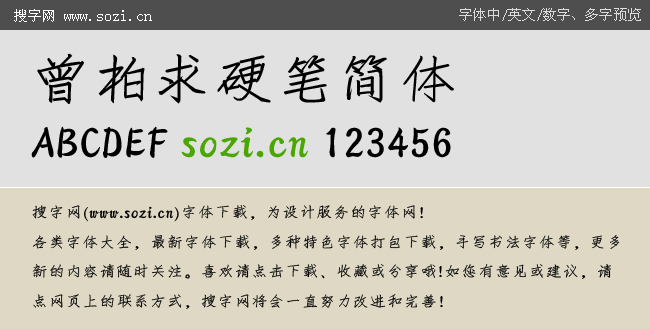
方正字跡-曾柏求硬筆簡體
搜字網(wǎng)給大家提供一款方正字跡-曾柏求硬筆簡體中文字體下載。方正字跡-曾柏求硬筆簡體是一款非常有特色手寫風(fēng)格書法字體,字形流暢大方,效果十分漂亮。此款字體適用于包裝設(shè)計(jì)、廣告設(shè)計(jì)、海報(bào)設(shè)計(jì)等視覺環(huán)境。